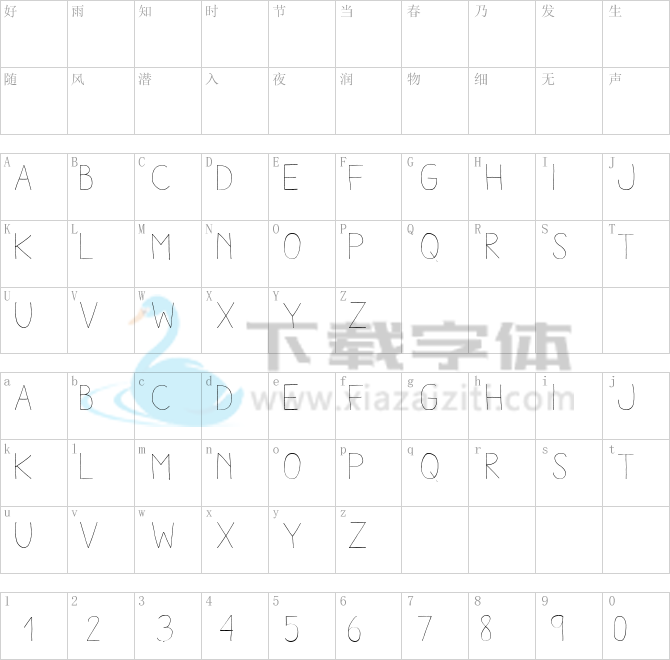
Aracne Light.ttf字体下载,这款字体结构工整、笔画清晰,兼顾美观与易读性,适用于标题、正文、海报、包装、LOGO 等多种场景。字形优雅稳定,风格百搭耐看,适配日常排版与创意设计,让文字呈现更舒适、更具质感。Aracne Light.ttf字体下载一笔一画,皆是细节,以均衡的比例、流畅的线条打造舒适视觉体验,字形端正大气,风格简约现代。无论是商业设计、品牌宣传还是日常排版,都能轻松驾驭,让文字更有格调与力量。Aracne Light.ttf字体下载字体下载。
Aracne Light.ttf字体属性详情
• 字体名称:Aracne Light
• 字体全名:Aracne Light
• 字重类:300